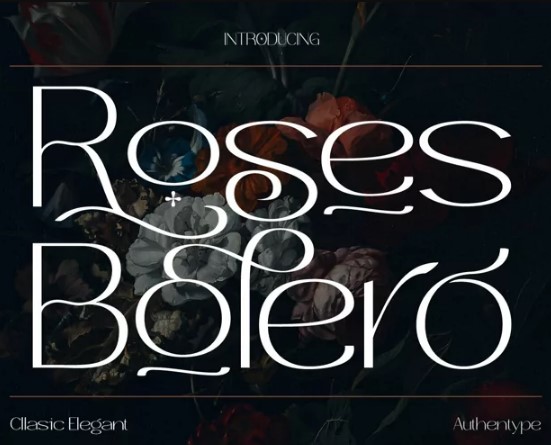
Fontbundles Roses Bolero Font
[Fontbundles] Roses Bolero Font
Roses Bolero Elegant Sans Serif - это безсерифный шрифт с полным набором заглавных и строчных букв, многоязычных символов, цифр, знаков препинания и лигатур. Розы Болеро элегантный шрифт без засечек классический и элегантный стиль для дизайна плакатов, журналов, красота брендинг с цветочной форме звездочки глиф подходит для вашей красивой и элегантной концепции дизайна.